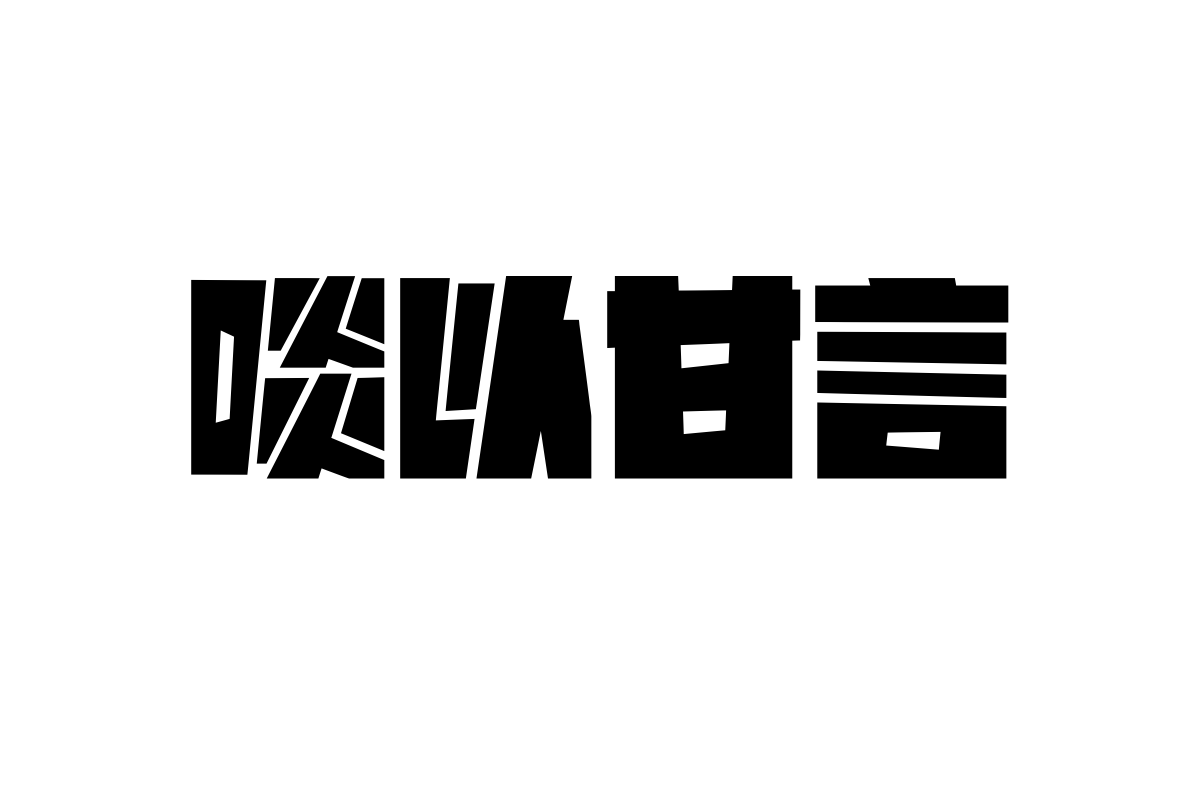
上首星岩体字体是一套由设计师张海兵设计的中文字体,具有独特的艺术风格和视觉效果。该字体采用了现代简约的设计风格,线条流畅、字形清晰,适合用于各种印刷品、广告、网站等场景。同时,上首星岩体字体也具有较高的可读性和辨识度,能够很好地传达出文本内容的主题和情感。总的来说,上首星岩体字体是一款非常实用的中文字体,适用于多种应用场景。